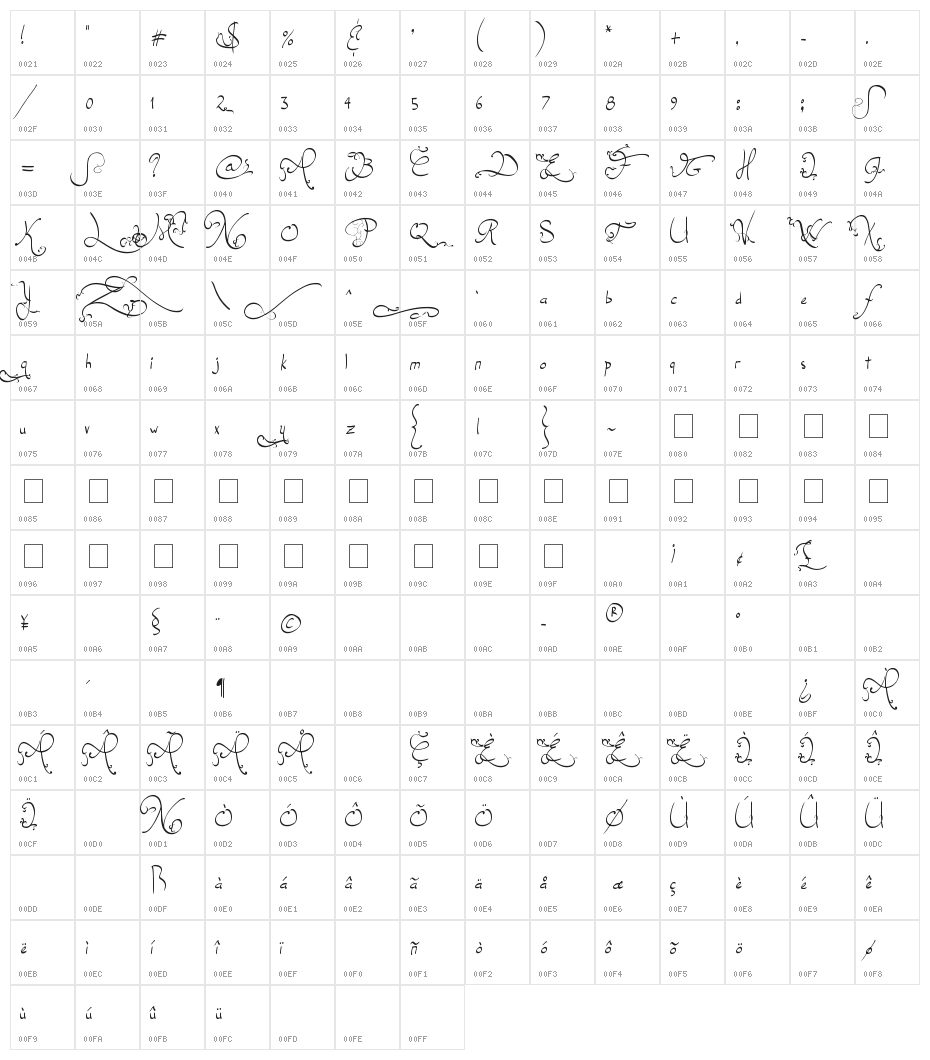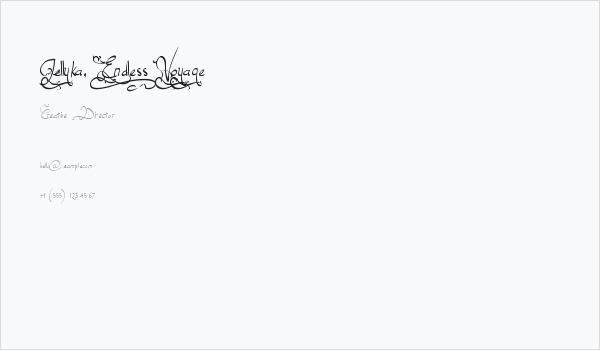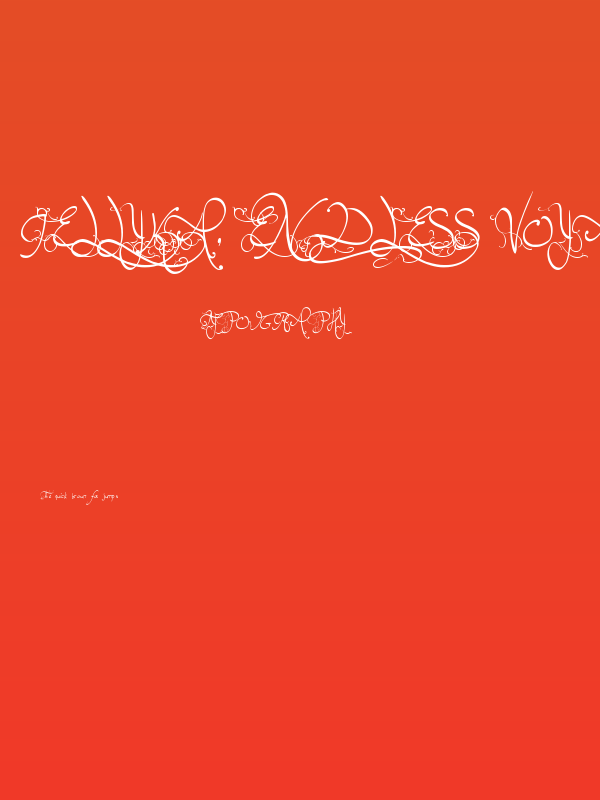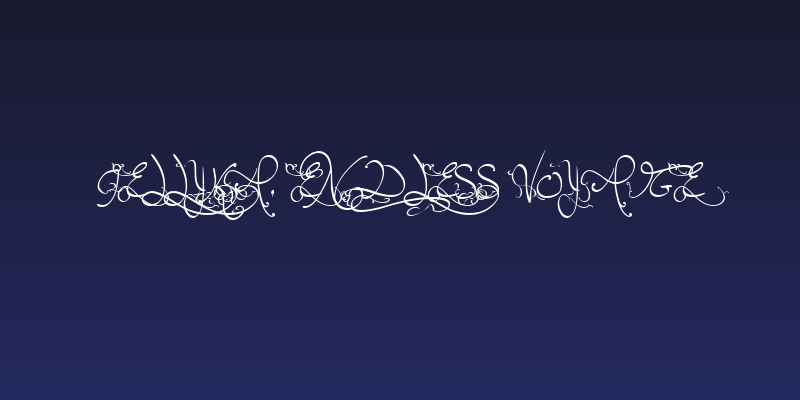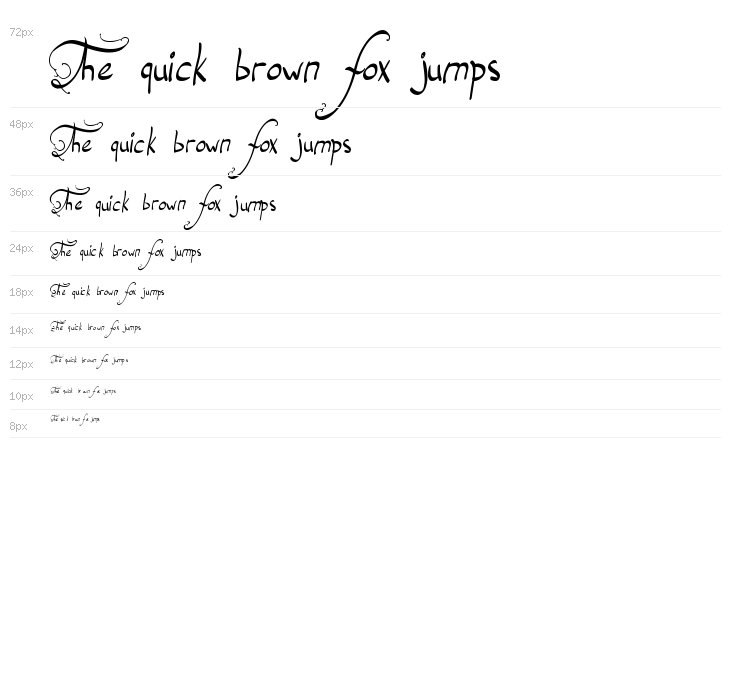
Jellyka, End_less Voyage Font
✎ Calligraphic
| Область применения | Invitations, Artistic projects, Branding |
| Рекомендуемые проекты | Ideal for wedding invitations, greeting cards, artistic posters, and branding materials that require an elegant touch. |